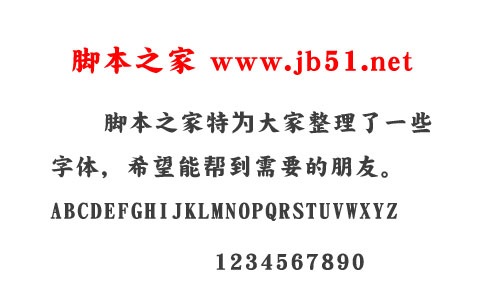
DF超極太楷書(shū)體字體(簡(jiǎn)稱(chēng):超極太楷書(shū)體)是一款非常不錯(cuò)的中文藝術(shù)字體,該字體線(xiàn)條粗細(xì)適中,字形大方得體,整體效果非常的出眾,并且字庫(kù)完整,可用于藝術(shù)設(shè)計(jì)、包裝印刷、簽名設(shè)計(jì)、圖形設(shè)計(jì)等領(lǐng)域,歡迎有需要的朋友前來(lái)下載。